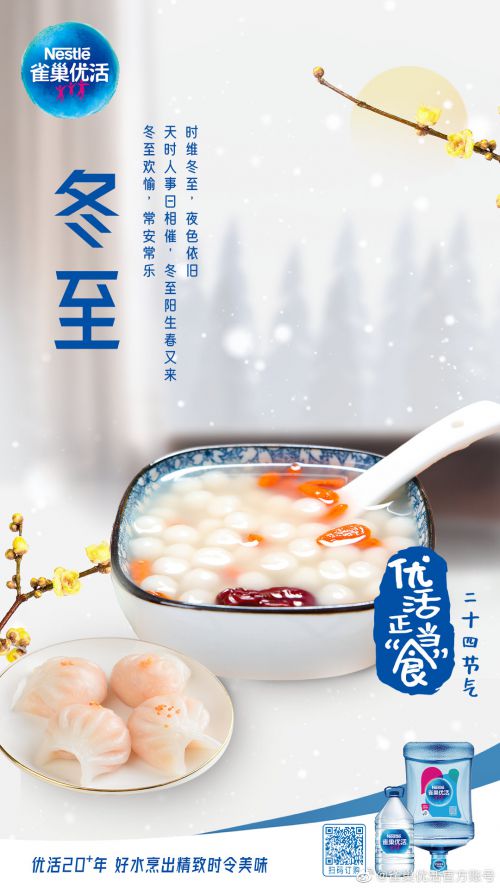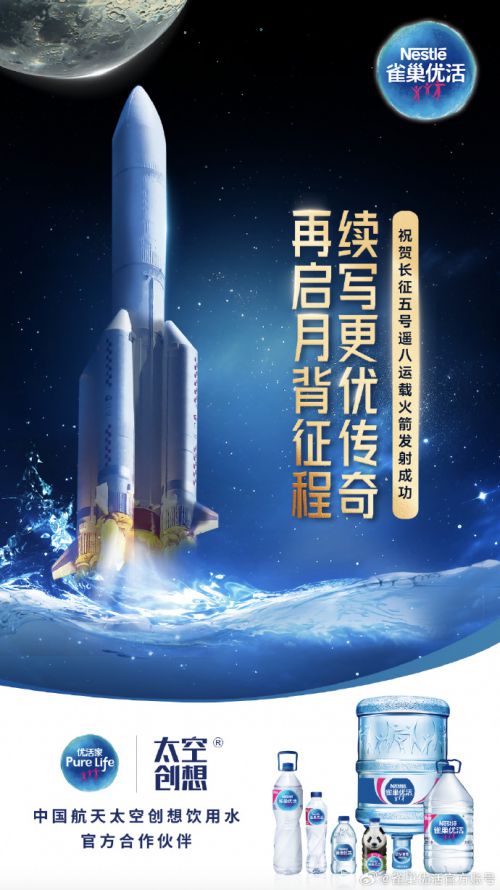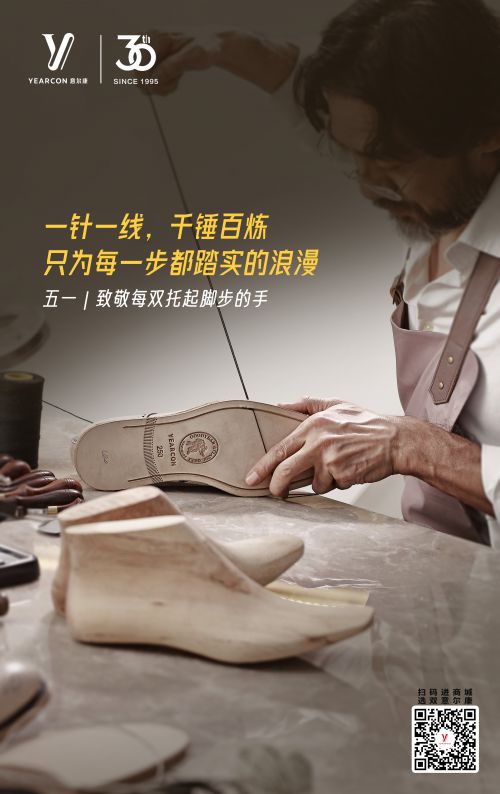
金山云技术体
金山云技术体是一款兼具现代科技感与设计巧思的创意字体,以简约风格为核心,为视觉设计注入利落的技术美学。 字形结构上,金山云技术体采用方正形态,重心居中平衡,中宫设计适中,整体布局稳重而不失灵动,展现出严谨有序的视觉秩序。笔型设计极具辨识度:笔画以直角线条为基础,搭配少量简洁的装饰元素,既保留了科技领域的理性与精准,又通过细节巧思避免了呆板;笔画粗细均匀适中,方头收笔的处理让字体更显力量感,而笔画间的断开连接设计,则进一步增强了字符的独立性与阅读清晰度。 作为免费商用字体,金山云技术体适用于科技产品界面、品牌宣传海报、数据报告标题等多元场景,其简约而富有张力的字形,能轻松驾驭现代设计对“科技感”与“简洁美”的双重需求,是设计师高效创作的实用之选。